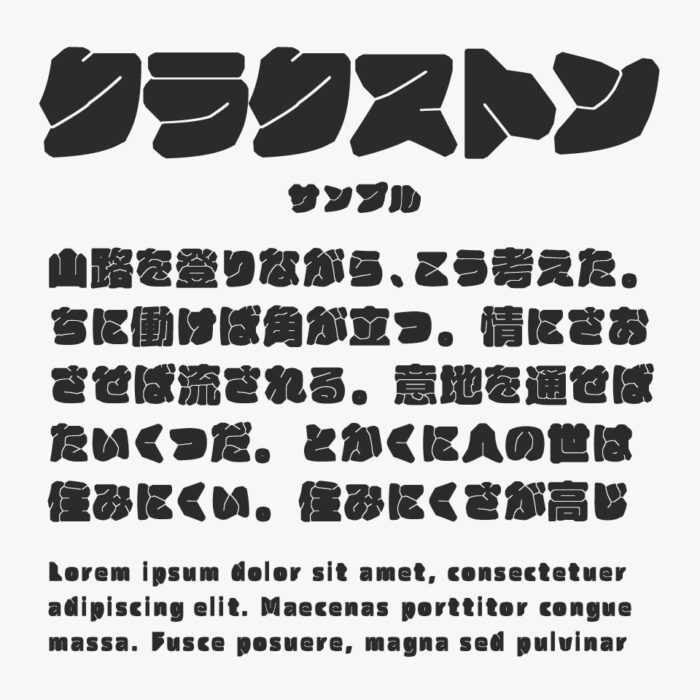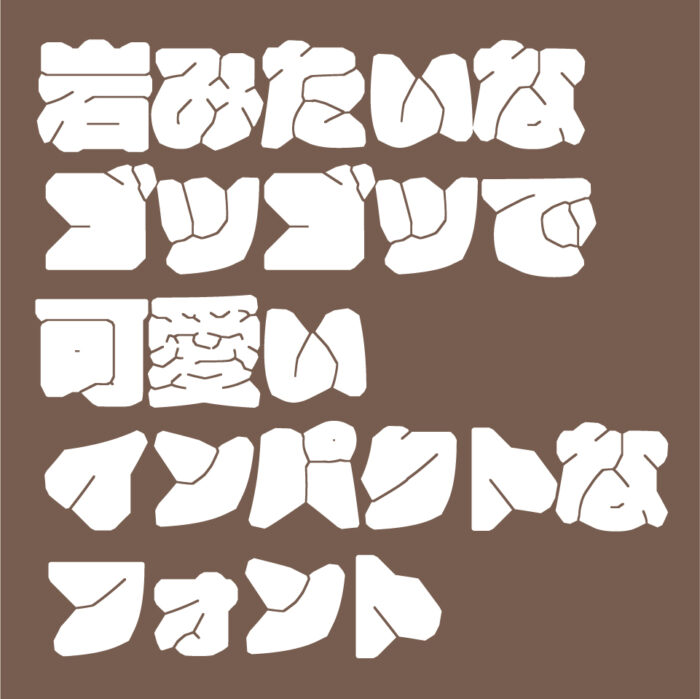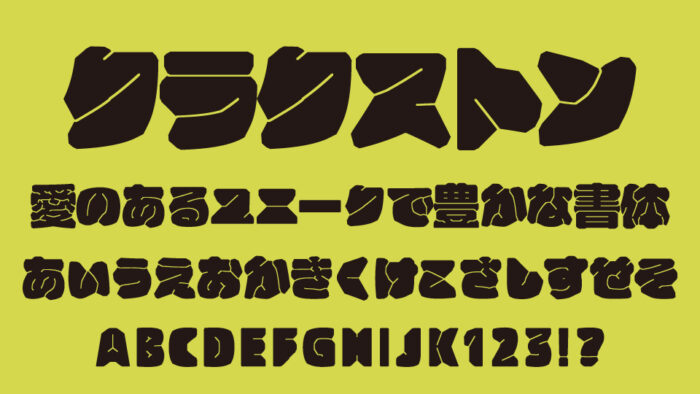
クラクストンは、余白をできるだけ排除し、太く膨張させてぎっしりと詰まったようなデザインフォントです。
岩を削って作られてたようなゴツゴツなフォルムが可愛さとカッコよさがあり、文字の隙間も可読がギリギリまで広げているのもユニークでとても面白いフォントです。
タイトルや見出しなどに取り入れるととってもインパクトがあり、目を引くフォントです。